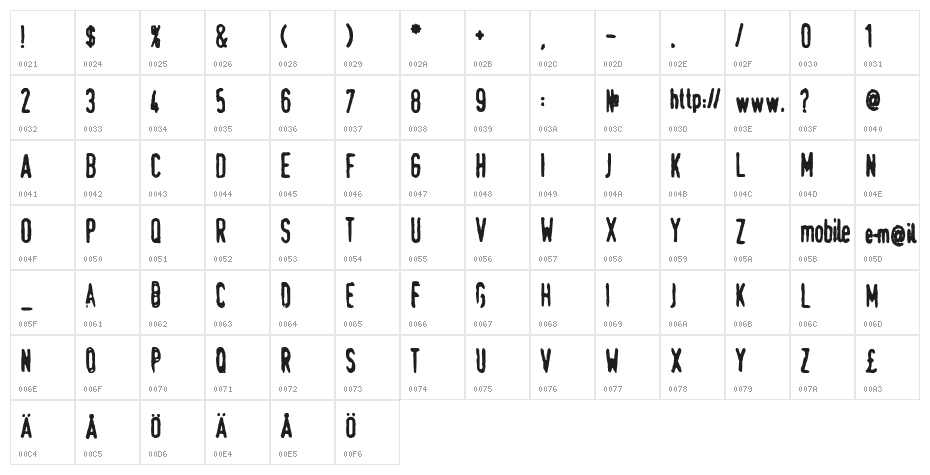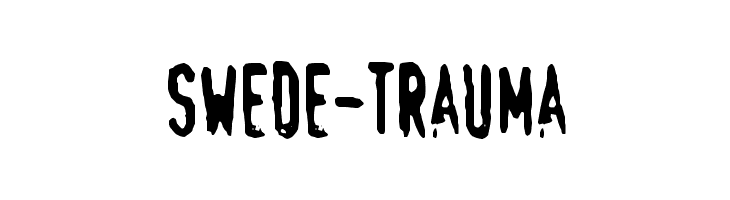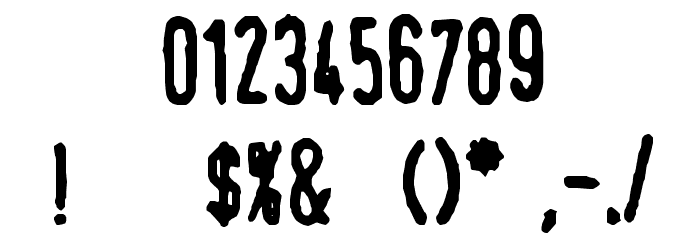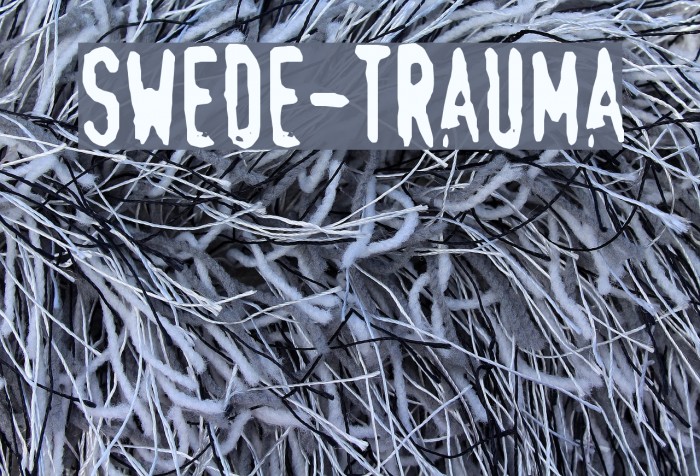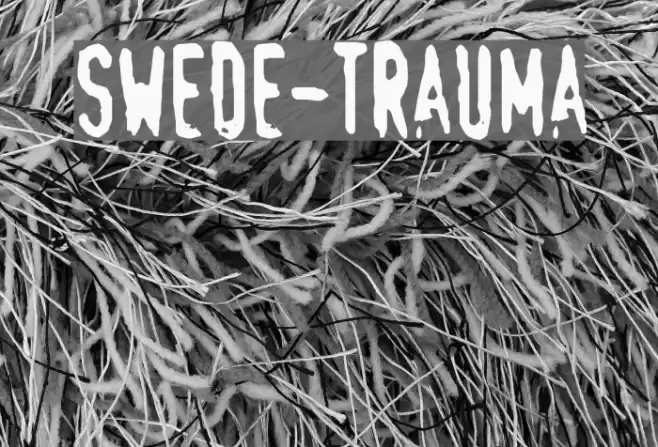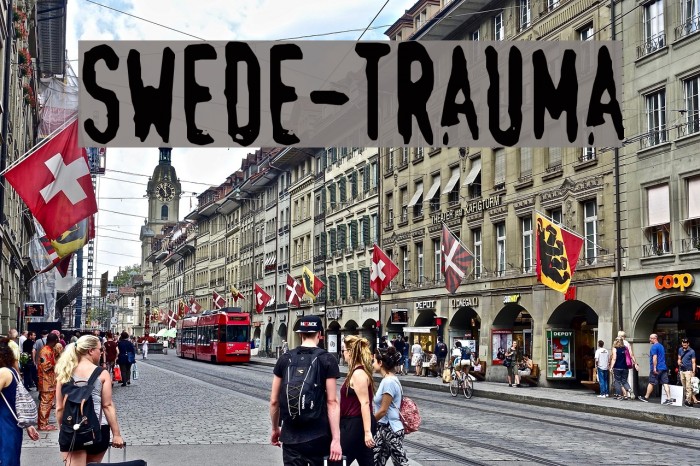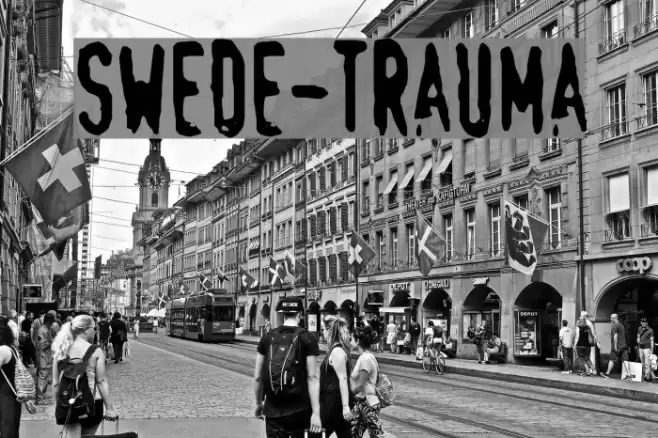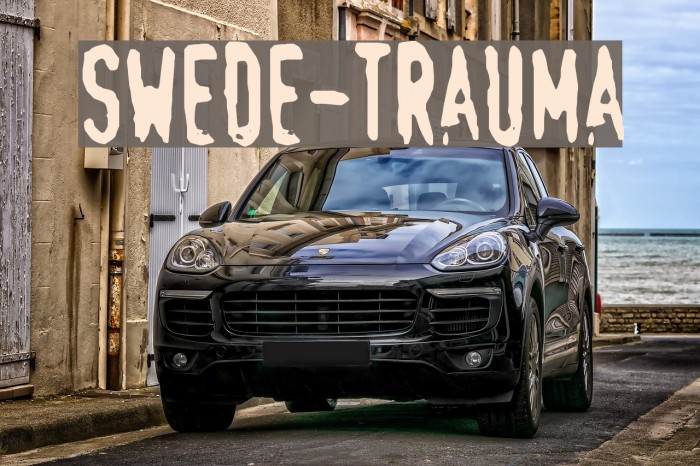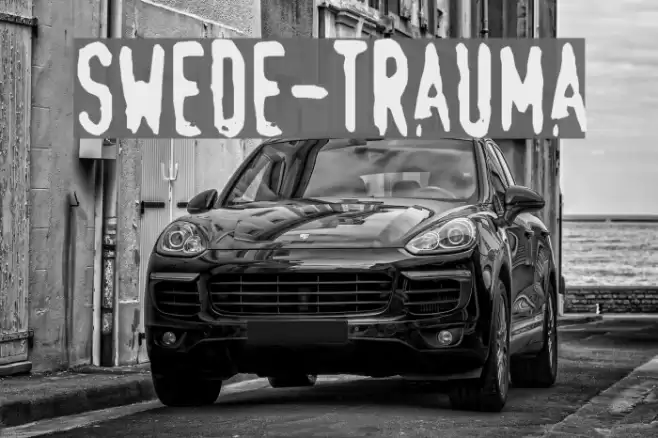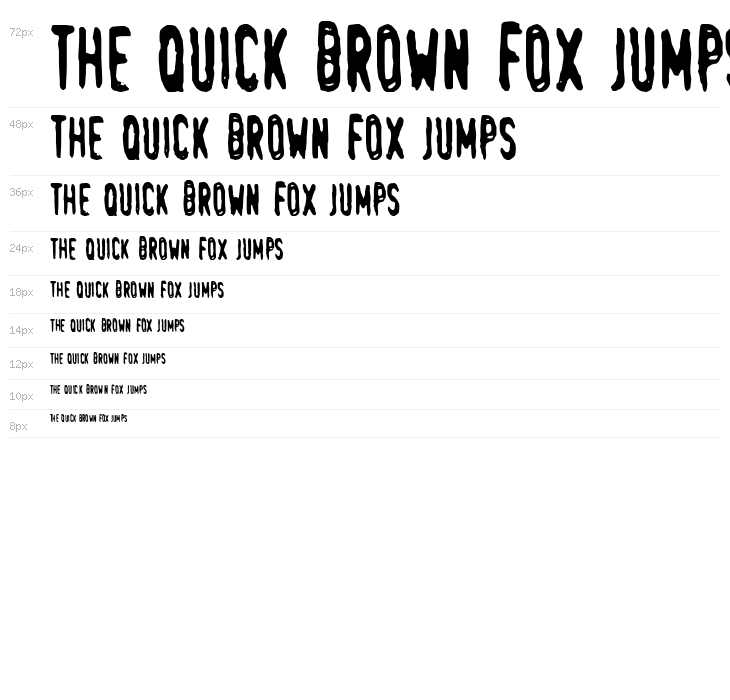
Swede-Trauma Font
✎ Capitals
| Catégories | Capitals |
| Style général | Vintage, Grunge |
| Projets proposés | Ideal for posters, album covers, branding for edgy products, or any design needing a bold, vintage touch. |